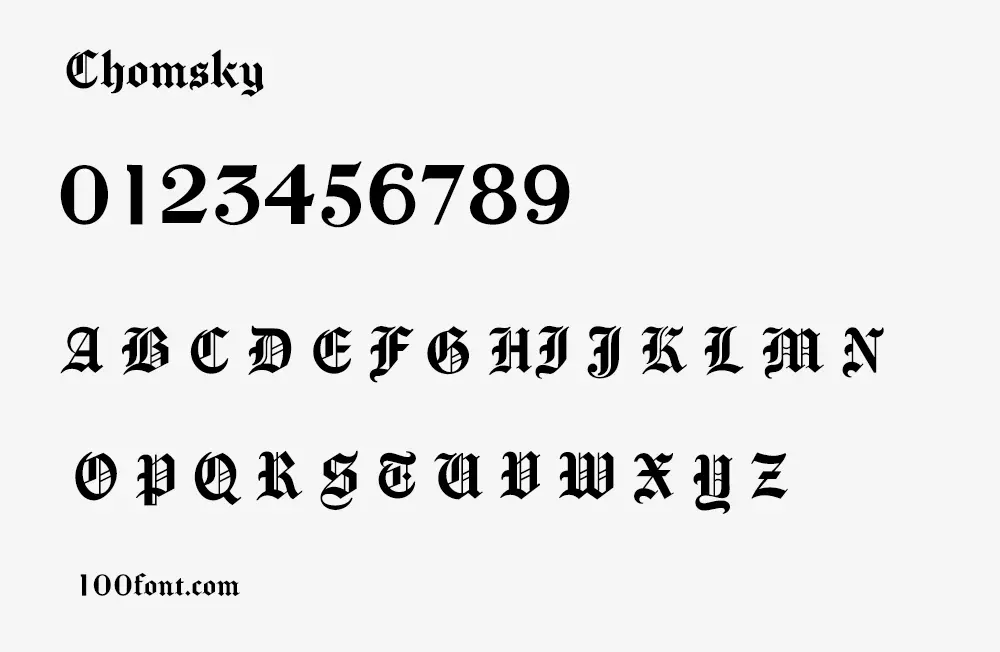
此字體不是紐約時報刊頭的精確副本。相反,它也旨在適合運行文本,因此我使用了更大的詞幹大小。一些字符之間的區別如下所示;上面是紐約時報的標誌,下面是喬姆斯基……:
This font is not an exact copy of the New York Times masthead. Rather, it aims to be suitable for running text as well, so I used a larger stem size. The difference between some of the characters are shown below; the N.Y.T. logo is above, and Chomsky below... :
我很驚訝,據我所知,我是第一個承擔這個項目的人。許多其他著名品牌,例如CNN、世嘉和可口可樂,都有向他們致敬的字體;事實上,這些字體中的大多數是在 Unicode 之前的時代製作的,並且在元數據方面以已不存在但曾經很突出的 Macromedia Fontographer 的名字命名;CNN 複製貓字體本身已經有 20 年曆史了。
I was quite surprised, that to my knowledge, I am the first to have undertaken this project. Many other famous brands, for example that of CNN, Sega, and Coca Cola have fonts in homage to them; indeed, most of these fonts were made in the pre-Unicode era and are branded in terms of metadata with the name of the defunct, but once prominent, Macromedia Fontographer; the CNN copy cat font is itself going on twenty years old.
也許是在黑色字體上創建額外字母的困難會嚇跑字體作者。也許是缺乏這方面的法律知識。不管怎樣,我相信我是第一個。
Perhaps it was the difficulty of creating the extra letters in a blackletter face that scared away would be font authors. Perhaps it was lack of knowledge about the law in this area. Either way, I do believe that I am the first.
當我給這個字體起名字時,我做了我認為是徹底的研究,以確保這個名字是獨一無二的。不幸的是,事實並非如此。該字體與由 Jimmy Ofisia 設計的T.26 Digital Type Foundry 的 Chomsky同名。
When I gave this typeface its name, I did what I thought to be thorough research to make sure the name was unique. Unfortunately, it was not. This font shares a name with Chomsky, by T.26 Digital Type Foundry, designed by Jimmy Ofisia.
因為現有字體來自 2009 年並且是專有的,所以我保持該字體的名稱相同。我相信用戶不太可能嘗試安裝這兩種字體,因為另一種字體不是免費的,所以默認情況下安裝的用戶群要小得多。此外,在我的字體發佈多年後更改它的名稱會破壞太多的用戶文檔並導致下游極度混亂。
Because the existing font is from 2009 and proprietary, I am keeping this font's name the same. I believe that it is very unlikely users will try to install both as the other font is not free so by default has a much smaller installed user base. Furthermore, changing my font's name many years after its release will break too many user documents and cause extreme confusion downstream.